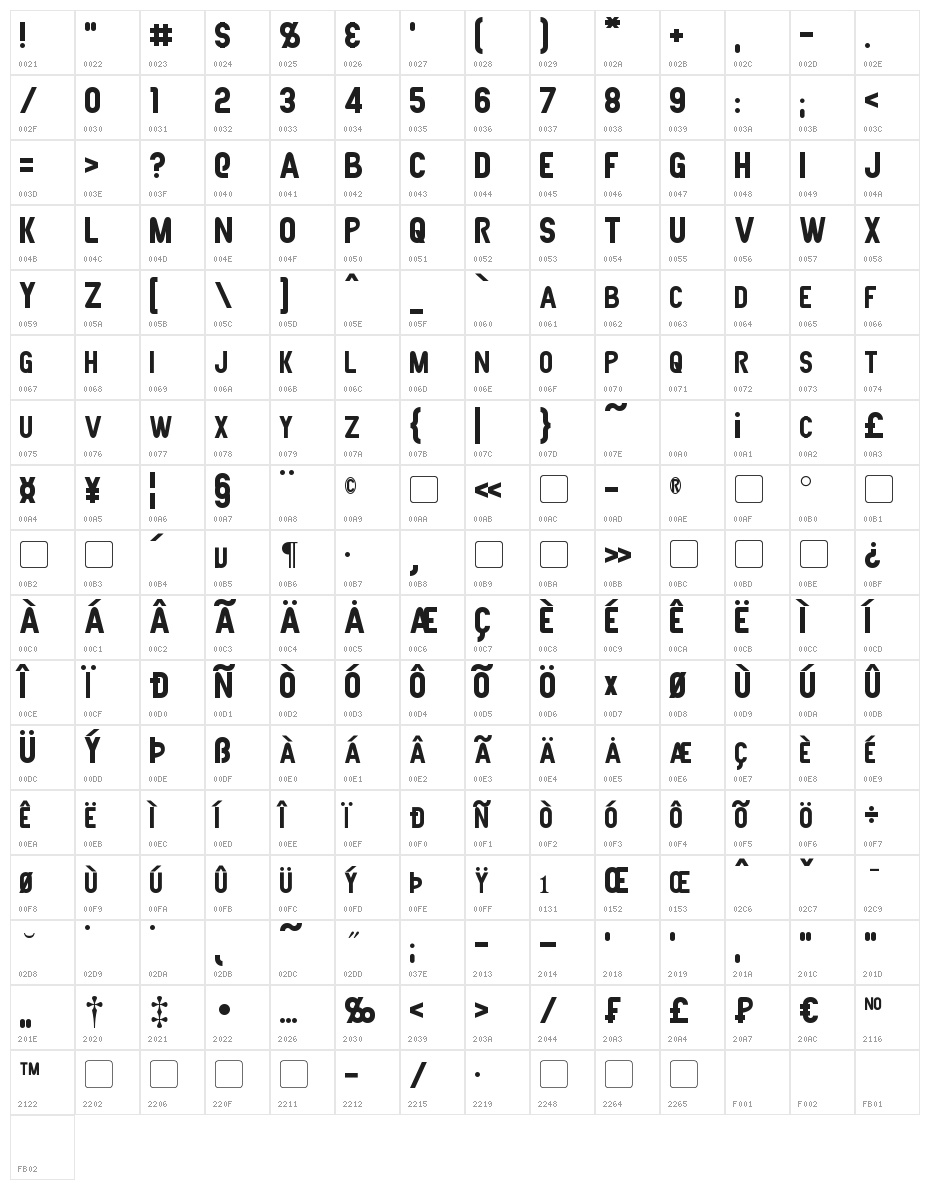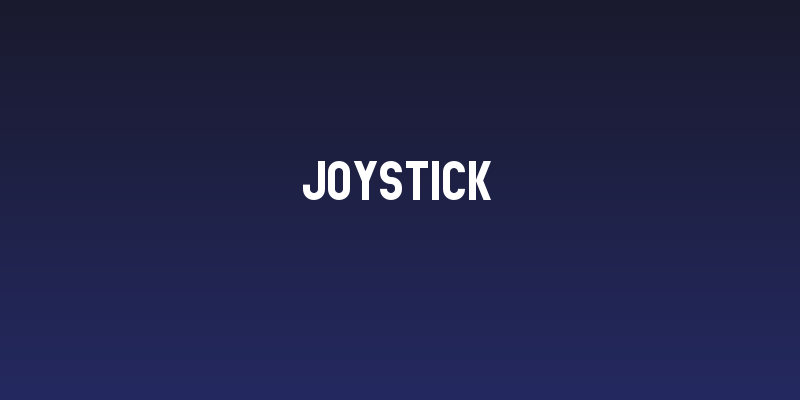
Joystick Font
| Vorgeschlagene Projekte | Ideal for branding, headlines, posters, and digital interfaces where a strong and modern typeface is needed. |